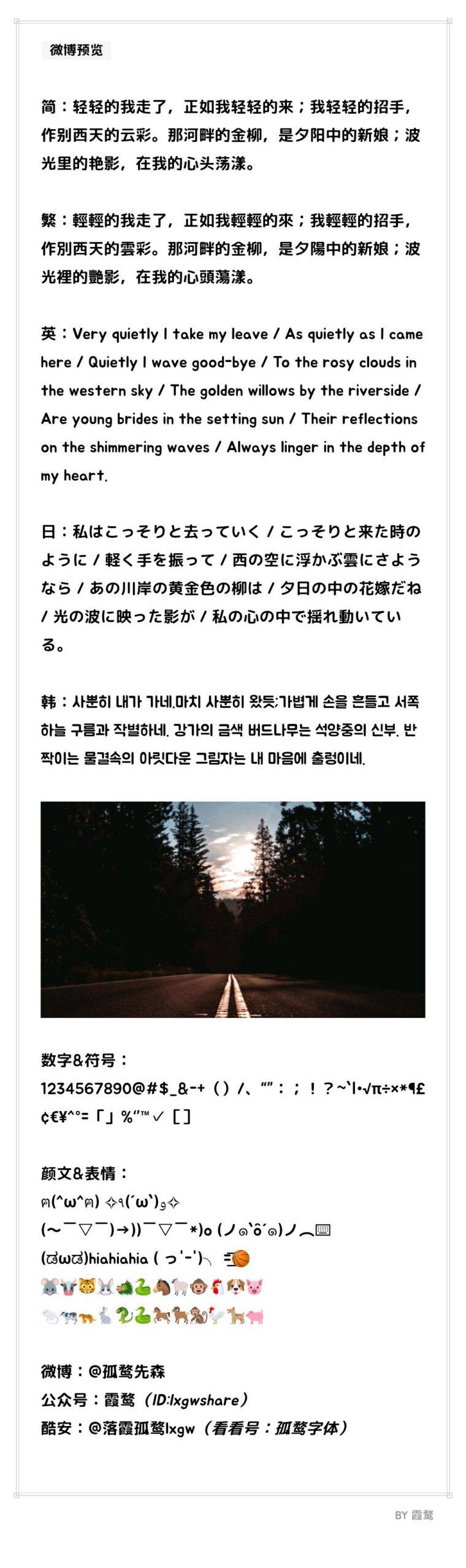
字体简介
微信预览展示《再别康桥》多语言诗句、数字与符号集、颜文表情及作者社交媒体账号。
制作该字体所利用的开源字体
原始字体
衍生字体
• 本字体基于日文字体改造,汉字写法大多遵循日文标准,未调整为中国大陆规范字形。如对字形有特定要求,请留意此点。
• 本字体在制作过程中移除了 OpenType 特性,高级排版功能(如竖排特性等)无法使用,敬请注意。
• 谚文(韩文)部分:因 Jua 仅包含 2367 个常用谚文音节,剩余音节由思源黑体填充,故本字体所包含的谚文字形存在风格不统一的情况,使用本字体显示韩文时可能出现视觉不一致的问题。